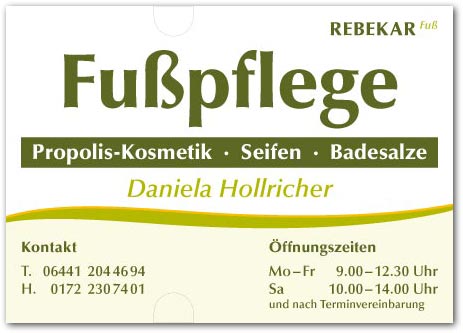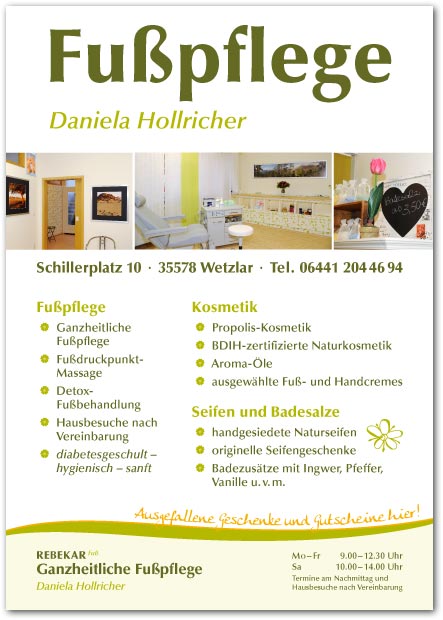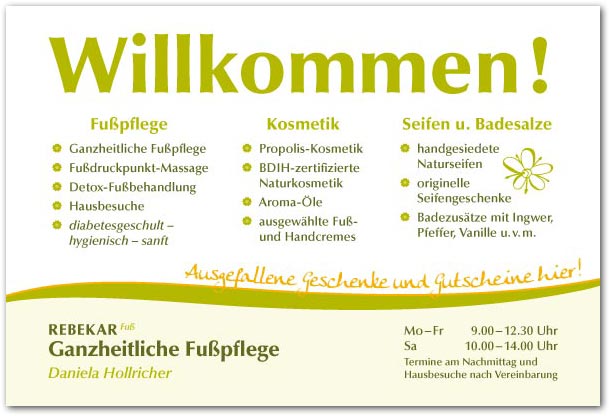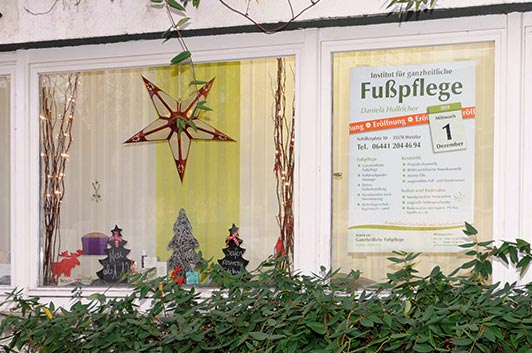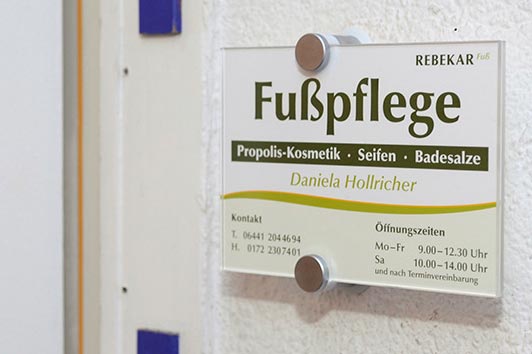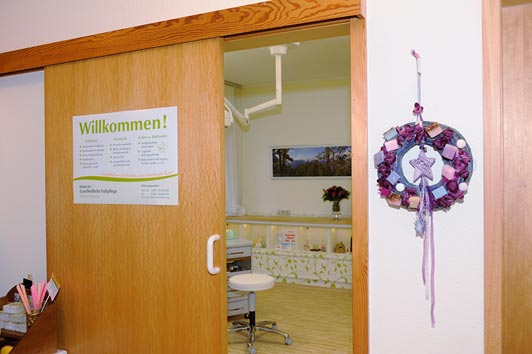
Schriftwahl für Gesundheitsbereich
was ich oft schon bei vielen bemerkt habe, dass sie es so machen wie der kunde es will und wie sein persönlicher geschmack ist, oft wird es aber dadurch schwammig und einfach nur »hübsch« ob man sich damit besser nach aussen präsentiert, würde ich bezweifeln.
Das heißt also, selbst wenn man sich an einen Profi wendet, kann es u.U. schiefgehen – je nachdem, wie durchsetzungstark man sich als Kunde ist und/oder wie leicht sich der »Profi« bequatschen läßt?
ich bin echt gespannt was dabei rauskommt aber das werden wir hier wie fast immer, niemals zu gesicht bekommen.
Andere (z.B. Stevo) fragen wenigstens höflich nach, ob das Ergebnis anschließend zu sehen sein wird, aber Du scheinst die Antwort ja schon genau zu kennen. Vielen Dank für diese freundliche Einschätzung …
das wort profis klingt so negativ, es gibt wie in jeder branche leute mit viel erfahrung, die sich gedanken machen aber auch welche die nach schema F arbeiten.
du würdest auch nicht jeden handwerker beauftragen, nur weil ein er logo und spruch »wir sind die profis« auf seinem transporter hat beauftragen um das bad fliesen zu lassen, oder?
für dich mag es alles aufregend sein und du brauchst hilfe hier nicht wir, trotzdem machen sich viele hier gedanken von den du profietieren kannst auch von den sachen die erstmal nicht so nach hilfe klingen, wenn man darüber nachdenkt, steckt da immer ein bisschen wahrheit drin.
ein tipp gebe ich dir, vergiss die ganzen softmaker/corel schriften, die sind sowas von angestaubt, inverstiere wenigstens 100,- euro für zwei, drei schriftschnitte.
schau dich zur inspiration mal hier um, es sind einige seiten mit tollen identity beispielen.
Ne, auch bei MyFonts bist Du nicht von selbst auf der sicheren Seite. Dahinter steckt die Firma Bitstream und die verkaufen halt, was ihnen Geld einbringt.
Die Optima ist sicher keine schlechte Schrift und natürlich auch insofern geeignet, als viele sie mit Kosmetik in Verbindung bringen. Aber: Willst Du so aussehen wie alle anderen, oder was besonderes haben? Wie Typografski schon gesagt hat, sind die Schriften, die als Klone von zig Firmen verkauft werden, alle alte Klassiker. Da sind natürlich schöne Sachen dabei, aber wir haben sie alle schon tausendfach gesehen.
Ihr könntet bei der farblichen Gestaltung – damit es nicht zu harmonisch Ton-in-Ton gerät – die Farbwelt etwas spannungsreicher machen, indem Ihr zu den Orange- und Sandtönen einen Hauch tiefes warmes Rotviolett kombiniert. Dabei sollte das Rotviolett aber nur als Akzent in der Gestaltung auftauchen, als kleines Ausrufezeichen sozusagen inmitten der orange-sandigen Farbwelt. Ich wünsche Dir viel Spaß bei der Gestaltung und Euch beiden viel Erfolg bei der Geschäftseröffnung. Es wäre schön, wenn Du uns später am grafischen Endergebnis teilhaben lassen würdest. :)
Hadder Rescht ... Ich kenne jedenfalls auch so ein, zwei Pappenheimer, die im Prinzip echt nix drauf haben, aber trotzdem seit Jahren überleben; die grasen eben die Kunden ab, die sich Mist für unverschämt kleines Geld andrehen lassen und den Unterschied nicht merken ... :neenee:
Bis jetzt ist das Sortiment an Druckerzeugnissen übersichtlich: Es gibt ein Türschild in A6 quer, ein »Willkommen«-Plakat (60cm × 40cm) für innen (und fürs Schaufenster), ein Info-Plakat in A1 fürs Schaufenster und Visitenkarten in 85mm × 55mm. Das Info-Plakat gab's zunächst in einer »Eröffnungsvariante« mit Datum 1. Dezember, inzwischen hab die Eröffnungsinfo allerdings durch ein paar Fotos von den Innenräumen ersetzt. Dieses Info-Plakat soll auch noch in einen Kundenstopper, sobald der dann mal geliefert ist.
Zunächst hab ich – weil's schnell gehen mußte und auch wegen der kurzen Korrektur- und Änderungsschleifen – alles auf meinem privaten A1-Fotodrucker gedruckt auf seidenmattem »Everyday«-Fotopapier, das für einen fairen Preis von ca. 42 € für 30,5 lfd. Meter (Breite 61cm) eine Top-Qualität liefert – auch, wenn es offiziell nur »Alltagspapier« ist …
Fonttechnisch hab ich mich für die Kombination aus Optima Demi und Optima Black entschieden, die Demi zusätzlich noch in kursiv. Das Ganze wird sparsam ergänzt durch die Anke Calligraphic.
Ist Dein Monitor kalibriert? Bei mir kommt's ganz gut raus (auch auf den Prints) …
Ja, ist kalibriert. Allerdings habe ich hier am Rechner gerade nicht die besten Lichtverhältnisse, da ist mir der Farbton durchgerutscht. :-)